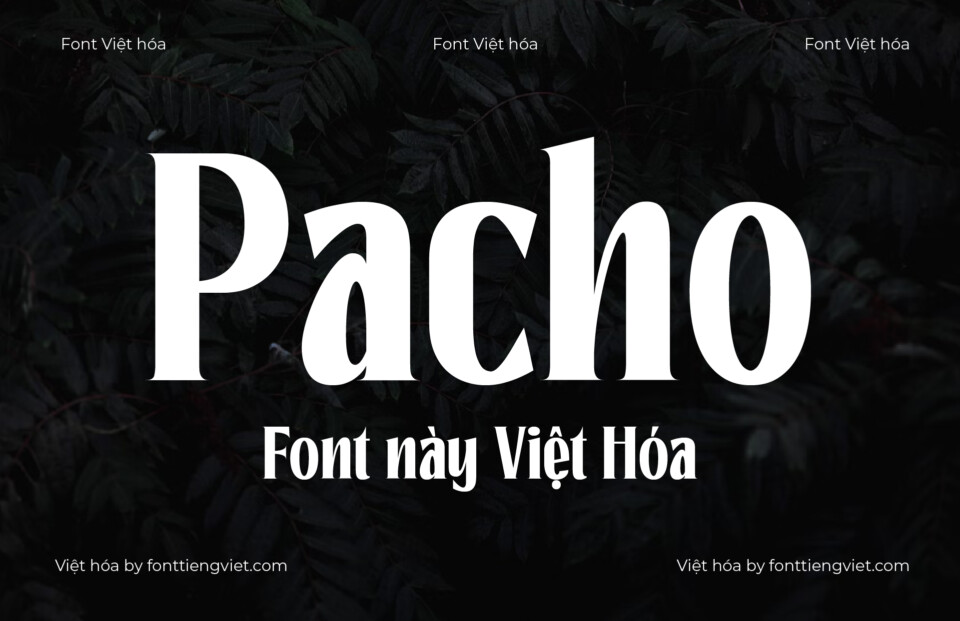
Giới thiệu bộ Font Việt hóa 1FTV Pacho độc đáo
Trong thế giới đồ họa hiện đại, việc lựa chọn Font Chữ phù hợp đóng vai trò then chốt giúp truyền tải thông điệp hiệu quả. Font Việt hóa 1FTV Pacho nổi lên như một sự lựa chọn hàng đầu cho những ai yêu thích phong cách mạnh mẽ, hiện đại nhưng không kém phần tinh tế. Đây là bộ phông chữ được tối ưu hóa hoàn toàn cho ngôn ngữ tiếng Việt, giúp người dùng loại bỏ nỗi lo về lỗi hiển thị dấu câu khi thiết kế.
Tại sao nên sử dụng Font Việt hóa 1FTV Pacho?
Bộ phông này sở hữu các đường nét dứt khoát, độ tương phản cao, rất phù hợp cho các tiêu đề lớn, banner quảng cáo hoặc bìa sách giáo khoa. Với cấu trúc hình học cân đối, 1FTV Pacho mang lại cảm giác chuyên nghiệp và uy tín cho mọi sản phẩm thị giác. Đặc biệt, việc cài đặt và sử dụng vô cùng đơn giản trên các phần mềm phổ biến như Photoshop, Canva hay Microsoft Word.
Ứng dụng thực tế của Font Việt hóa 1FTV Pacho
Nhờ tính linh hoạt cao, Font Việt hóa 1FTV Pacho thường được giáo viên và học sinh ưu tiên dùng trong các bài thuyết trình PowerPoint hoặc làm báo tường. Khả năng đọc tốt ở nhiều kích thước khác nhau giúp nội dung luôn rõ ràng và bắt mắt. Ngoài ra, các nhà thiết kế tự do cũng có thể khai thác bộ font này để tạo ra những logo mang đậm dấu ấn cá nhân hoặc các bộ nhận diện thương hiệu sáng tạo.
Để đạt hiệu quả thẩm mỹ tốt nhất, bạn nên kết hợp 1FTV Pacho với các phông chữ không chân (sans-serif) mảnh hơn cho phần nội dung chi tiết. Hãy đảm bảo bạn tải bản Việt hóa chuẩn để tận hưởng đầy đủ các ký tự đặc trưng của tiếng Việt một cách trơn tru nhất.